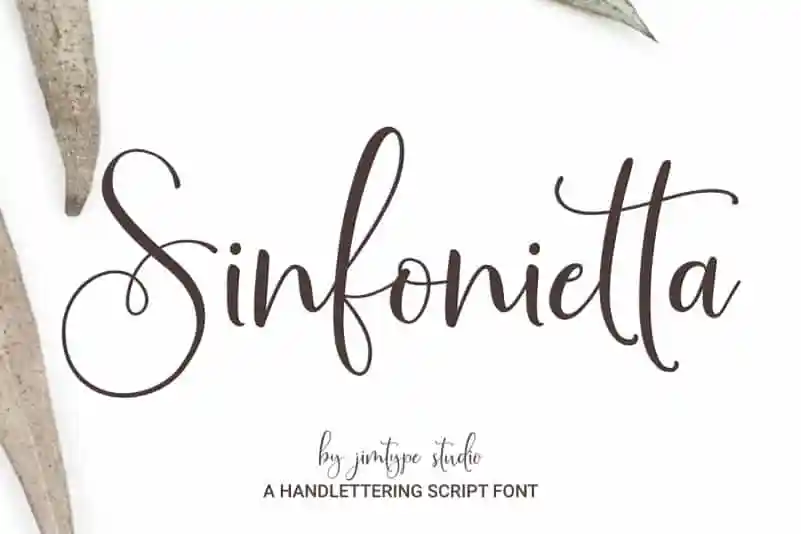
Sinfonietta Modern Script Font – Fonte Grátis
Sinfonietta Modern Script Font
Sinfonietta Modern Script Font é uma fonte escrita a mão simples e encantadora que se destaca por sua versatilidade. Suas linhas delicadas e arredondadas criam um toque romântico, perfeito para dar um toque especial em cartões de aniversário, convites de casamento, criações de arte para estação ou até mesmo postagens nas redes sociais. Sua elegância se aplica a uma ampla gama de projetos gráficos, tornando-a uma opção ideal tanto para quem quer um ar retrô quanto para aqueles que buscam algo mais contemporâneo e sofisticado. Com sua fácil escrita à mão, você pode criar designs personalizados sem esforço, entregando aos seus clientes ou seguidores uma experiência de design única e envolvente.